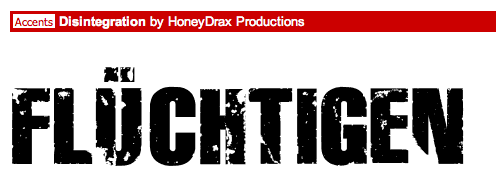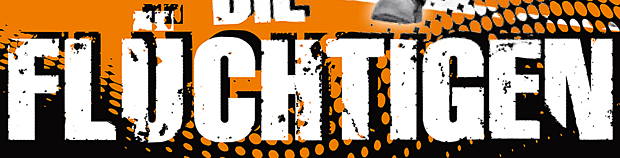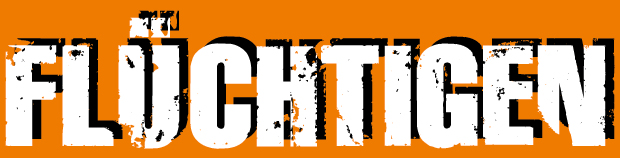
Hallo zusammen.
Ich muß eine Typo nachbauen (siehe Anhang).
Kann mir jemand einen Tipp geben, wie man das macht, damit der Text so grungy aussieht (Tutorial etc.)
Hallo WriteRoom,
also normalerweise kenne ich das so, dass man die Störformen, die die Buchstaben so kaputt aussehen lassen sollen, als Vektorformen baut und dann aus den in Pfade konvertierten Buchstaben herausschneidet. Das ist zwar ordentlich Arbeit, aber wenn man sich die Formen separat abspeichert und im Archiv ablegt, dann hat man sie beim nächsten Anwendungsbedarf parat. Ich habe mal eine Zeit lang Motive für T-Shirt-Prints einer großen Modemarke entwickelt und habe gestaunt, wie viele solcher Strukturen die als Vektordateien archiviert und in der Schublade liegen hatten. Die haben sie bei Bedarf einfach hervorgeholt und über neue Designs drübergelegt. Fertig war der Vintage-Look.
Die Formen kann man entweder frei erfinden, oder man nimmt sich ein Foto mit einer geeigneten Struktur, öffnet es in Photoshop, wandelt es in Graustufen um und zieht den Hell-Dunkel-Kontrast extrem an und speichert das Bild ab. In einem dafür geeigneten Programm kann man die Struktur vektorisieren und die so gewonnenen Formen dann wie gewünscht über dem Schriftzug platzieren und aus den Buchstaben herausschneiden. Fertig. :-)
PS: Ich bin sicher, die Kollegen hier im Forum haben noch mindestens zwölf weitere Methoden auf Lager, wie man an die Sache herangehen kann. :nicken:
Ich habe so etwas bisher nur mit Gimp gemacht. Dort gibt es eine Funktion, die sich „Plasma“ nennt, in Photoshop gibt es vermutlich etwas ähnliches. Damit kann man, je nach Einstellungen, zufällig verrauschte Muster erzeugen, beispielsweise dieses:
Mit dem Farbwähler kann man dann, je nach eingestellter Genauigkeit, Bereiche aus dem erzeugten Bild auswählen und die entstandenen Muster (die sich natürlich auch automatisch vektorisieren lassen) weiterverwenden.
Man kann natürlich auch das ganze erzeugte Bild über die Schrift legen oder als Ebenenmaske benutzen.
Oder: du setzt den Text ab, druckst ihn einmal aus (vorzugsweise auf einem Laserdrucker) anschließend knitterst du so lange an dem Papier herum bis du das gewünschte Ergebnis hast, scannst das Ganze dann ein und fertig. Weiteres Verfahren und Vektorisierung wie bereits beschrieben.
Oder: du verwendest einen Grunge-Pinsel, die überall im Netz zu finden sind, die gibt's sowohl für ai als auch für ps. Alles in allem keine große Sache.
@ Koni: Ist natürlich auch eine Variante, sich schon vorkonfektionierte (d.h. »vorzerstörte«) Schriften zu installieren... . ;-) Zwei oder drei aus dem schier unüberschaubaren FreeFont-Angebot gefallen mir ganz gut.
Ist natürlich auch eine Variante, sich schon vorkonfektionierte (d.h. »vorzerstörte«) Schriften zu installieren..
Dachte, du mußt die gepostete Typo nachbauen.
Mein ( nicht zugelassener) Link führt zu genau der Schrift, die Du eingangs gepostet hast.
Ah, jetzt kapier’ ich. Anfangs bekam ich nämlich immer die Fehlermeldung, daß Safari die Website nicht öffnen kann und ich wurde immer zu einem FreeFont-Portal geleitet, wo es Unmengen von »zerstörten« Schriften gibt. Also danke, Koni, habe die Schrift gefunden und installiert! Eigentlich kinderleicht... . ;-)
Ah, voilà. Mal schnell quick und dirty zusammengebastelt, aber die Richtung stimmt. Danke, Koni.